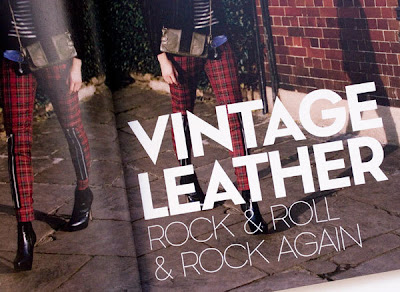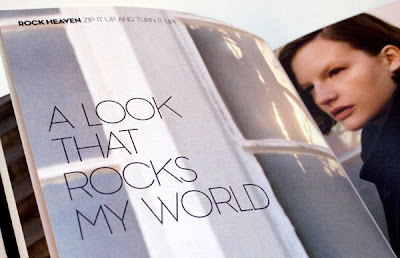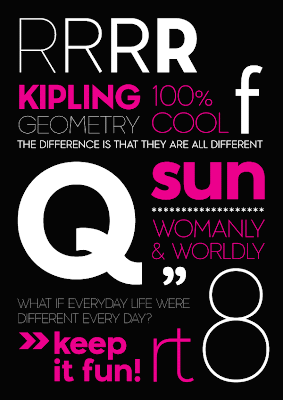
Fuentes personalizadas por Kipling, la marca internacional de complementos de moda.
BaseLab es el departamento de diseño tipográfico de BaseDesign iniciado en 2005, de acuerdo con su pagina web, trabajan desde Barcelona hasta cualquier rincón del mundo, especializados en fuentes personalizadas para clientes en diferentes rangos, aparte también trabajan con logotipos y cuestiones de programación.
Como podemos observar en las revistas, es una tipografia trabajada especificamente a todo lo relacionado con la moda, es una tipografía elegante, similar a la helvética pero diferente a muchas, ya que el departamento de diseño esta bien orientado trabajando su tipografia de acuerdo a los intereses del cliente, así como vender sus fuentes, lo cual es una aportación directa a los diseñadores tanto experimentados como nuevos.